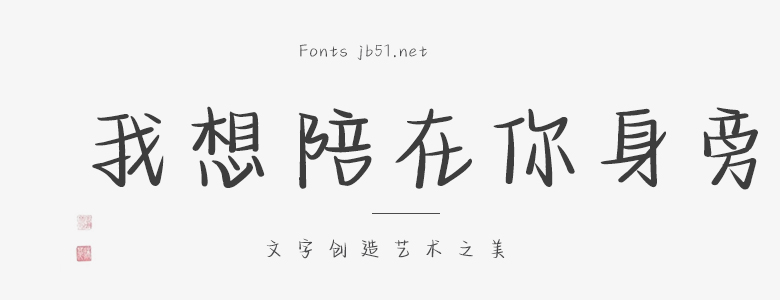
我想陪在你身旁
“我想陪在你身旁”是一款独特且富有情感的字体。设计这款字体的主要目的是为了传达出深情、陪伴与温暖的信息。其线条柔和,形态优雅,独具特色,能轻易地吸引人的目光。 “我想陪在你身旁”的字母和汉字设计都充满了独特性。每个字母都有其独特的形状和大小,这使得整个文本看起来非常有机和自然。汉字的设计则充满了流动性,它们似乎从内部散发出一种温暖的光芒,给人一种舒适和亲密的感觉。 这款字体的笔触特别细腻,设计中有种牵连不断的情感。无论是单独的字母还是整个句子,都似乎在讲述一个关于陪伴和深深思念的故事。这种情感的表达方式,使得“我想陪在你身旁”不仅仅是一种字体,更是一种情感的传达。 从视觉的角度来看,“我想陪在你身旁”提供了一种新颖的阅读体验。它的艺术性使得任何文本都显得更加吸引人。无论是用于浪漫的卡片,还是用于温馨的书籍,这款字体都能完美地呈现出陪伴与深情的氛围。 总的来说,“我想陪在你身旁”是一款富有艺术性和情感性的字体。它的设计独特,优雅自然,极具吸引力和深情。无论是作为主体字体还是装饰元素,它都能在各种场合中发挥出其独特的魅力,为你的设计增添深度和温度。